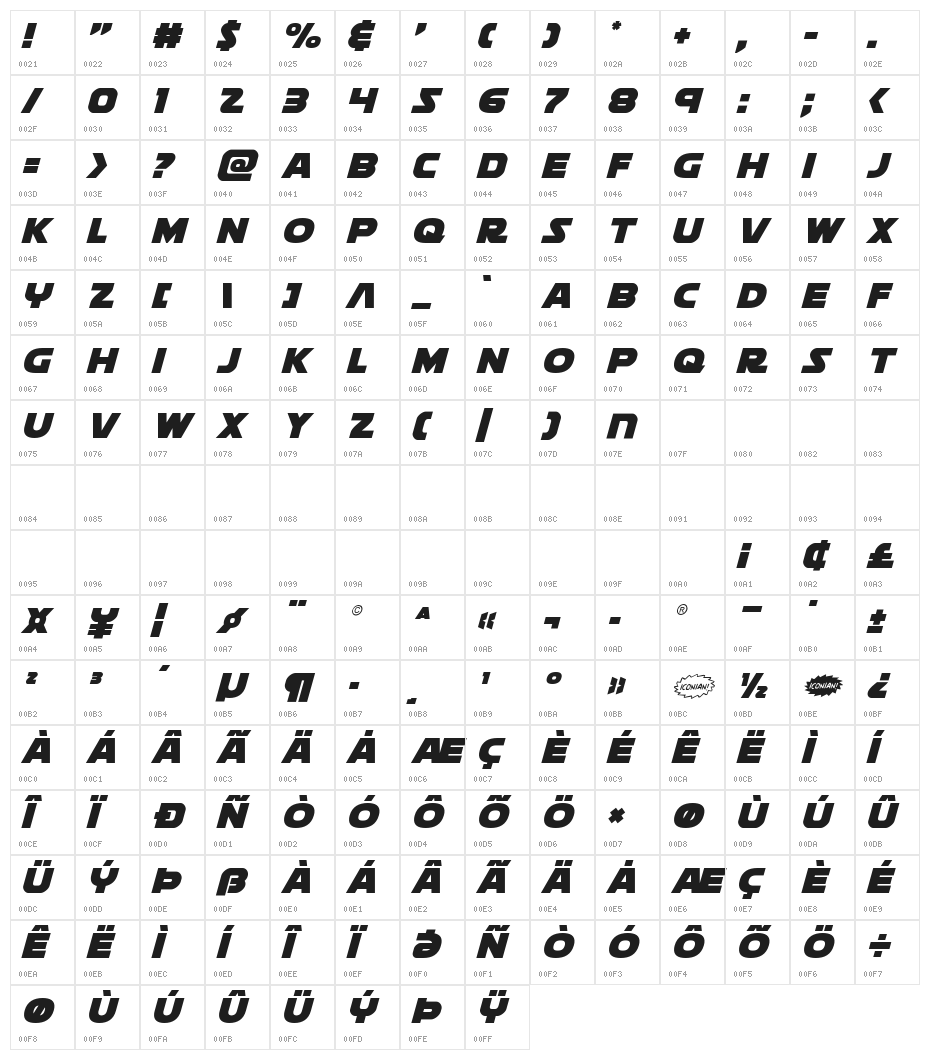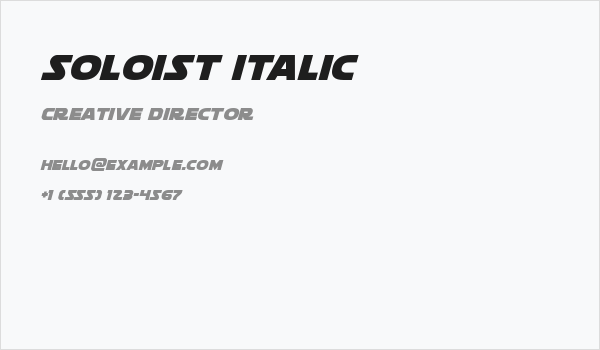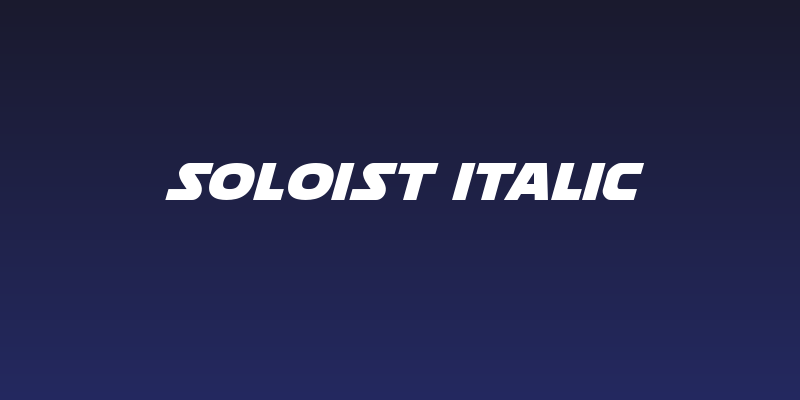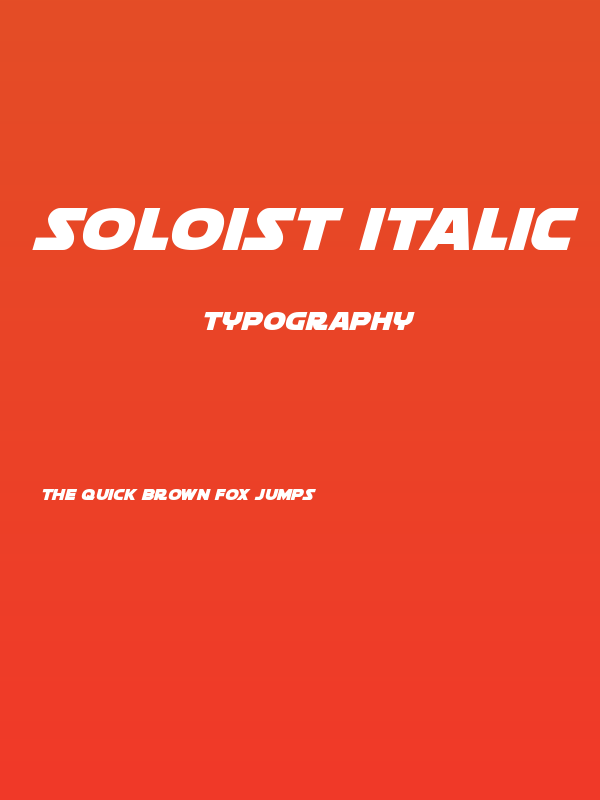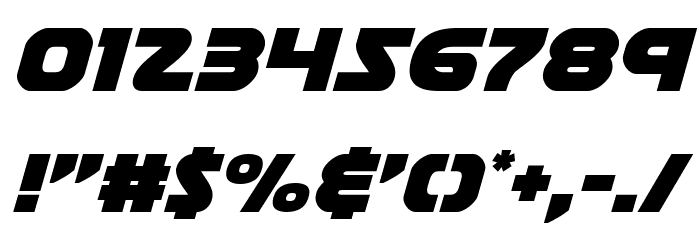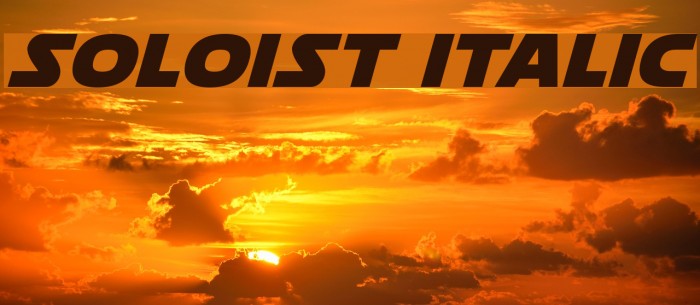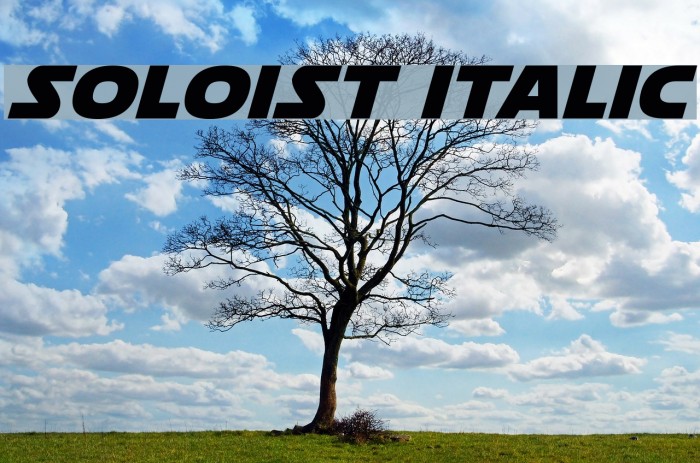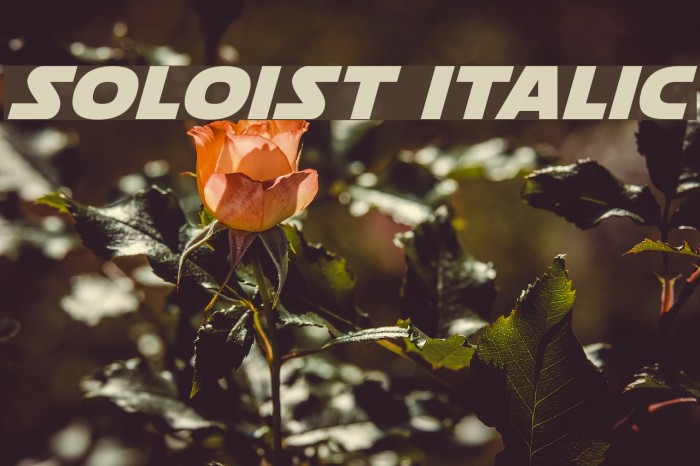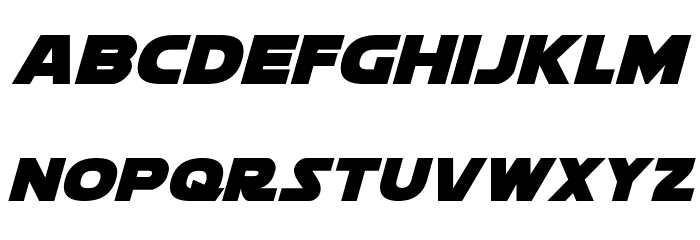
Soloist Italic Font
| Proyectos propuestos | Ideal for sports branding, dynamic posters, modern advertisements, and any project requiring a bold statement. |